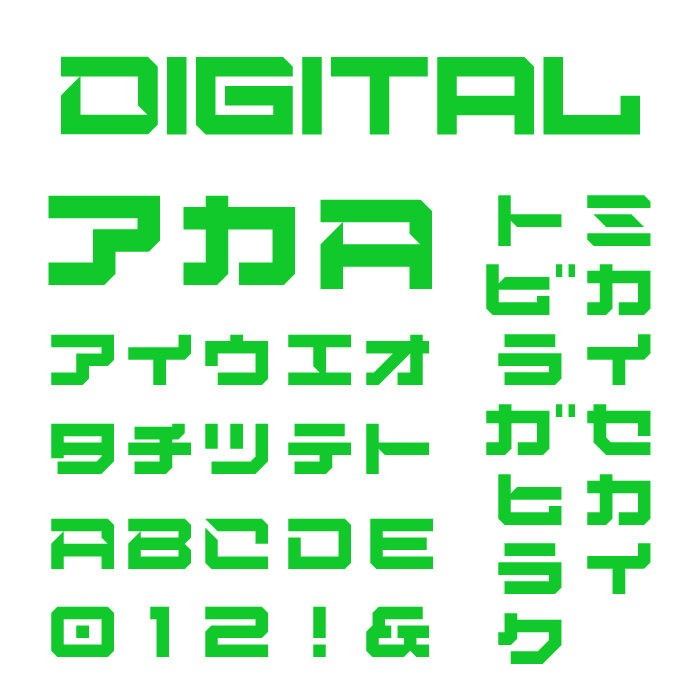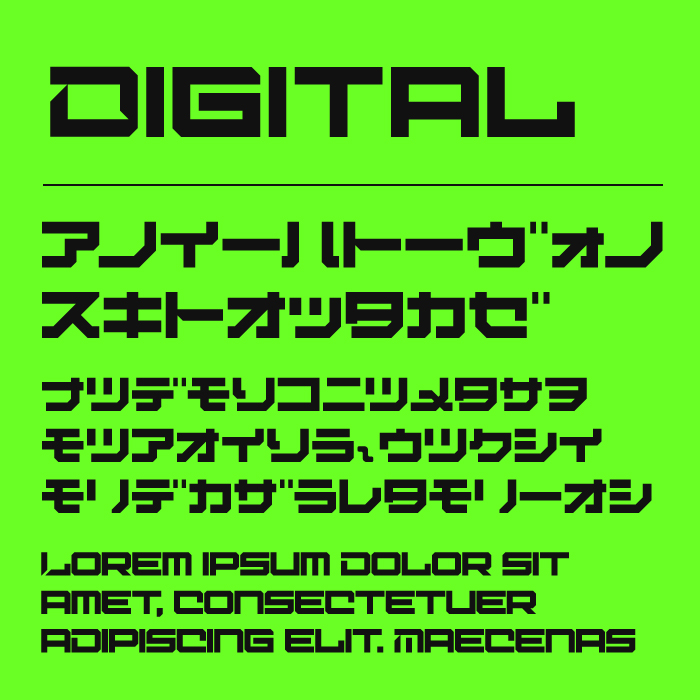
Digital Desolation Plus (デジタルデゾレーションプラス) フォントは、近未来的で無機質な魅力を放つ、カクカクして横に長めに作られているクールなデジタルフォントです。
シュッとした斜線や鋭角が多用されており、視覚的な緊張感とシャープさを強調されたカッコよさがあり、まるで機械の動作音が聞こえてきそうな、無駄を削ぎ落とした美しさがあるデザインです。
カタカナや英字も含め全体のデザインに統一感があり、サイバーな世界観に深くフィットします。ゲーム、テクノロジー、AI、仮想空間といったテーマのデザインで抜群の効果を発揮するフォントです。
収録文字は、カタカナ・アルファベット・数字・記号が収録。